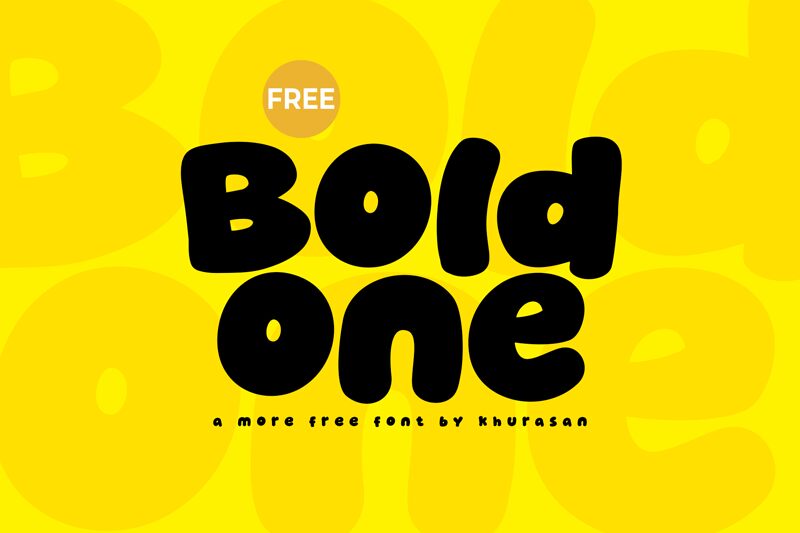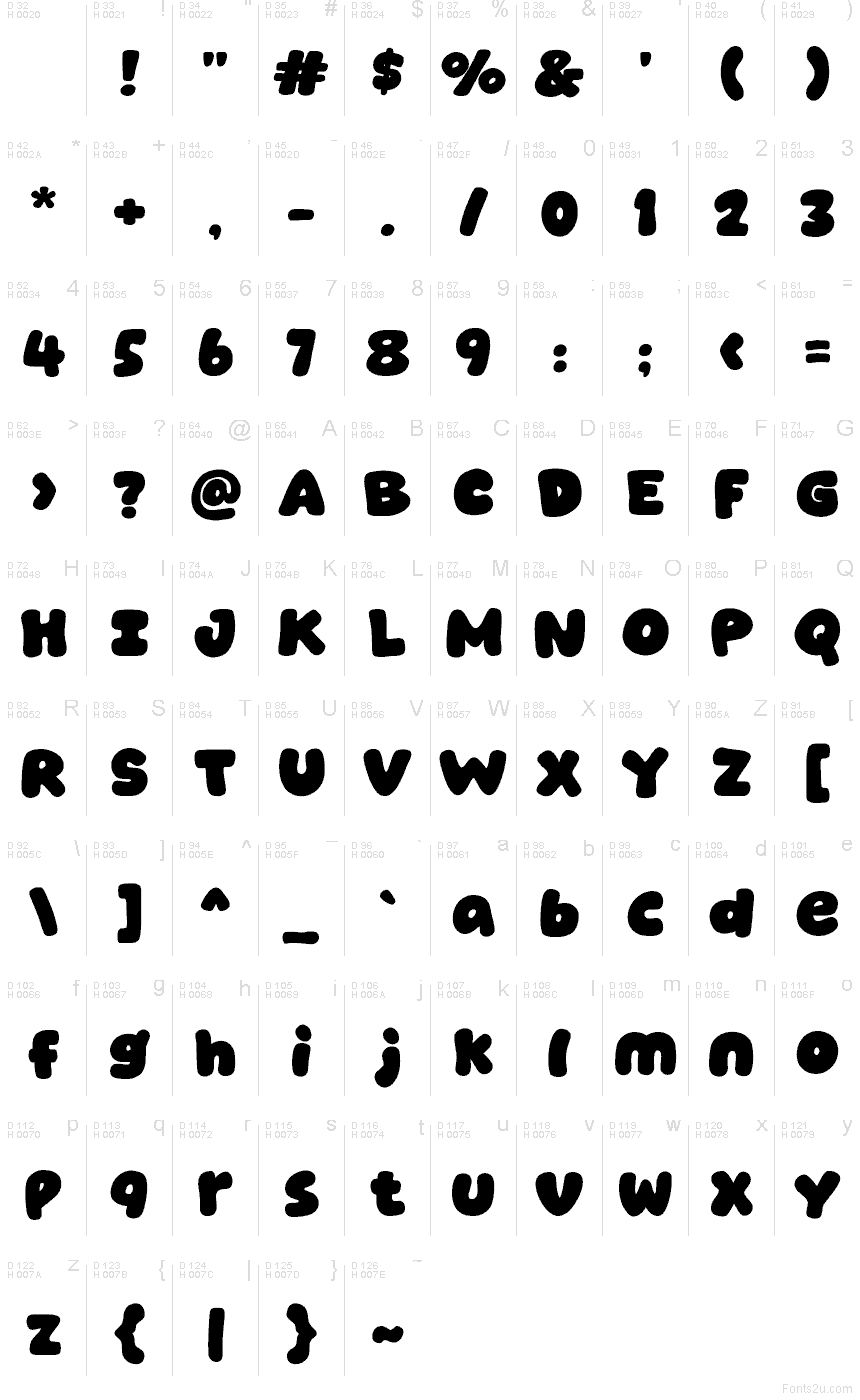
Boldone od Khurasan je bezplatné kreslené titulkové písmo s veľkými, nadýchanými písmenami a veselým retro komiksovým švihom. Tvary pôsobia mäkko a nafúknuto, s výraznými zaoblenými líniami, mierne rozkolísaným rytmom a kompaktnými rozostupmi, vďaka čomu nápisy pôsobia priateľsky, bláznivo a dynamicky.
Hodí sa na obaly, obálky detských kníh, branding občerstvenia, hravé plagáty, miniatúry na YouTube či párty pozvánky, kde potrebujete okamžitú dávku priateľského dojmu namiesto strohej elegancie. Keďže sú písmená také bucľaté a tesne pri sebe, Boldone skvele funguje aj v krátkych titulkoch a skiciach log, ktorým dodáva nafúknutý, ručne kreslený charakter.